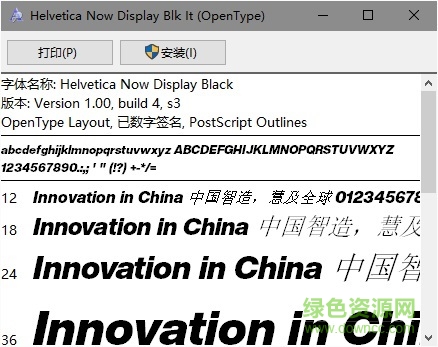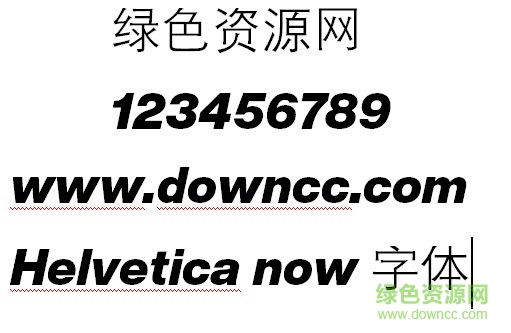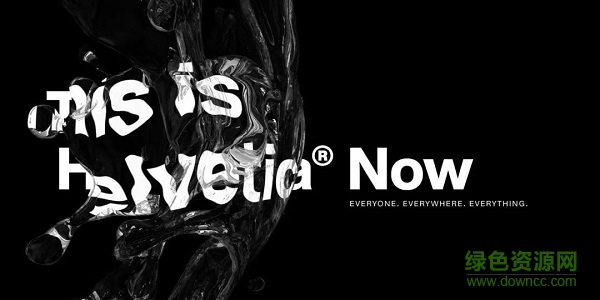
helvetica now字體是由Monotype公司最新發(fā)行的一款英文字體,Helvetica now字體是專為移動電子屏幕打造的字體,這個系列的字體有三種不同光學尺寸可以選擇,有需要的用戶趕快來綠色資源網(wǎng)免費下載使用吧!
經(jīng)典字體 Helvetica 由瑞士設計師Max Miedinge和Eduard Hoffmann于1957年設計完成,是一種廣泛使用于拉丁字母的無襯線字體。Helvetica被視作現(xiàn)代主義在字體設計界的典型代表,讓讀者在閱讀的時候專注于文字所表達的內容,而不會關注文字本身所使用的字體。
2019年4月,Monotype 公司正式發(fā)布了這款全新的字體“Helvetica Now”。Helvetica Now字體包含字母、數(shù)字、標點符號總共近4萬個,共有三種形體,分別為:Micro、Display和Text。